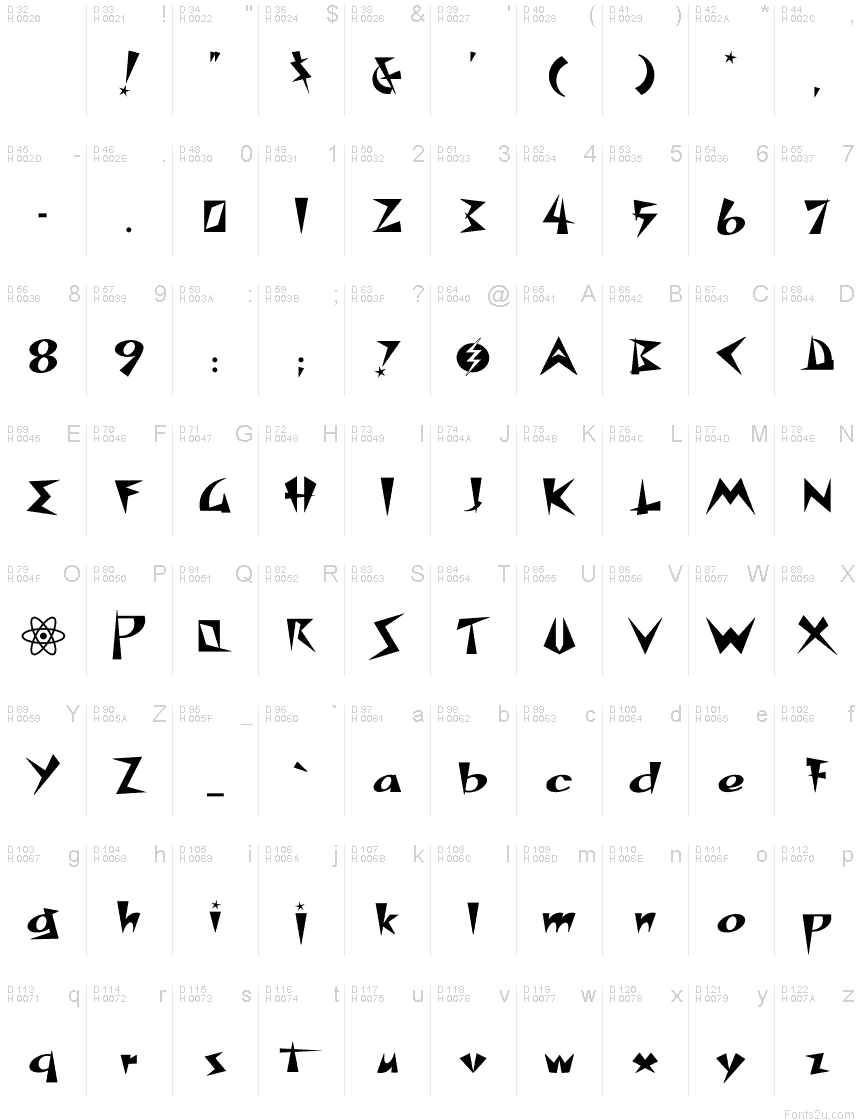
Space Patrol autorstwa Nicka Curtisa to darmowy, komiksowy font w stylu retro sci-fi, z charakterystycznym, luźnym polotem futurystyki z dawnych seriali kosmicznych. Litery łączą szerokie, zaokrąglone krzywizny z nagłymi, ostrymi cięciami, na czele z dramatyczną literą S przypominającą błyskawicę, która nadaje skośny, dynamiczny rytm reszcie słowa.
Świetnie odnajduje się na nagłówkach plakatów, okładkach komiksów, brandingu w stylu arcade, planszach tytułowych i grafikach eventowych, gdzie pasuje odrobina kosmicznego kampu. Jako darmowy font sprawdzi się również w logotypach, krótkich nagłówkach i przyciągających wzrok hasłach, ponieważ same litery niosą ze sobą ruch i charakter, nie potrzebując wiele tekstu.